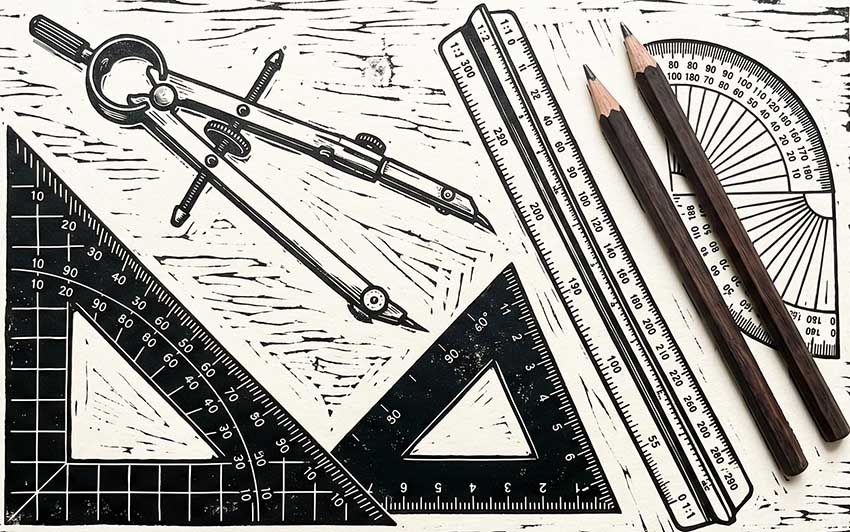
Pismo Techniczne jest szeroko stosowane w różnych dokumentach, w tym w rysunkach technicznych, instrukcjach montażu, specyfikacjach i innych, związanych z projektowaniem, produkcją i eksploatacją urządzeń. Jest to specjalna czcionka, zaprojektowana z myślą o polskich normach i standardach w dziedzinie techniki. Czcionki pisma technicznego mają wiele cech charakterystycznych, które umożliwiają czytelne przekazywanie informacji.
Techniczne PRO to komplet fontów z krojem popularnego pisma technicznego w 6 odmianach. Wszystkie fonty są wielojęzyczne, zawierają znaki CE (m.in. polskie), zachodnie, Cyrylicę i greckie.